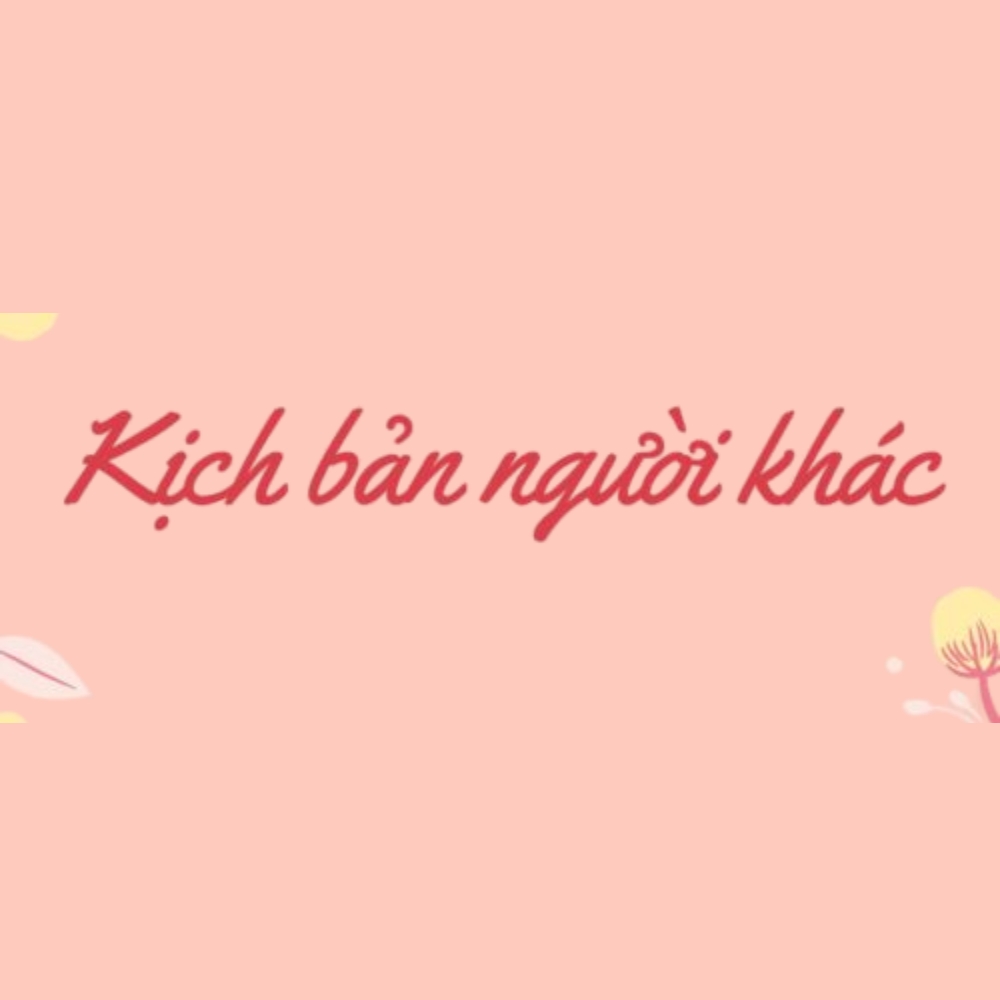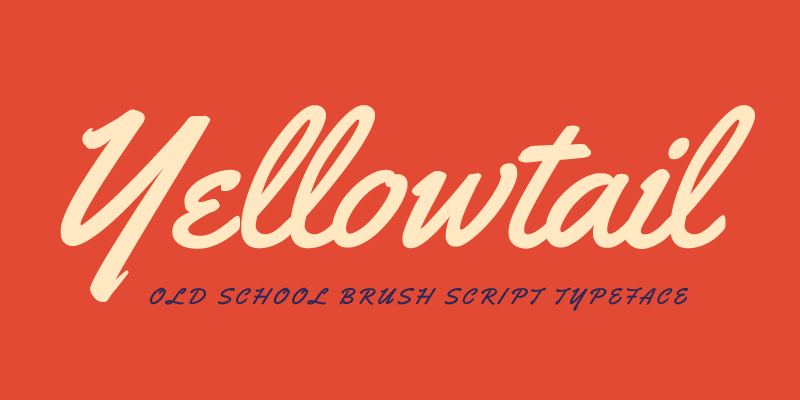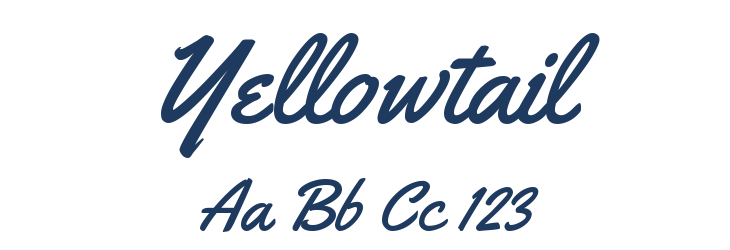
Tải 20+ font Việt hóa Yellowtail nghệ thuật và bắt mắt
Yellowtail mang đến vẻ đẹp cổ điển của những năm 1930, gợi nhớ đến phong cách vẽ bảng hiệu bằng cọ dẹt đầy tính nghệ thuật. Sự kết hợp giữa những đường nét Script nghiêng và sự dứt khoát của nét cọ đã tạo nên một bộ font chữ có sức hút riêng, vừa phóng khoáng vừa chỉn chu. Sự ra đời của font Việt hóa Yellowtail giúp các nhà sáng tạo tại Việt Nam có thêm một lựa chọn hoàn hảo cho các thiết kế mang hơi hướng hoài cổ mà không lo ngại về vấn đề lỗi ký tự tiếng Việt.
Sự độc đáo trong cấu trúc của font Việt hóa Yellowtail
Nét đặc trưng của Yellowtail nằm ở phong cách brush script với các đường nối ký tự mượt mà, tạo nên một dòng chảy văn bản tự nhiên như được viết tay bởi những nghệ nhân vẽ biển hiệu chuyên nghiệp. Font Việt hóa LNTH Yellowtail đã được tinh chỉnh bộ dấu tiếng Việt một cách khéo léo, đảm bảo các dấu thanh không làm phá vỡ cấu trúc nghiêng đặc trưng của bộ chữ. Điều này giúp văn bản luôn giữ được sự cân đối và tính thẩm mỹ cao trên mọi ấn phẩm thiết kế.
Bên cạnh đó, độ dày của nét chữ trong Yellowtail được tính toán để mang lại khả năng hiển thị ổn định. Dù được sử dụng ở kích thước lớn trên các bảng hiệu hay kích thước nhỏ trong các bản in, font chữ này vẫn giữ được độ sắc sảo và dễ đọc. Đây là phương án phù hợp cho những ai muốn tìm kiếm sự giao thoa giữa nét đẹp truyền thống và hơi thở hiện đại trong các sản phẩm đồ họa và kiến trúc.
Font Việt hóa LNTH Yellowtail đẹp 01
Font Việt hóa LNTH Yellowtail đẹp 02
Phân loại phong cách Flat-brush Script / Vintage
Phiên bản Việt hóa LNTH (Linh Nguyen Thai Hoa)
Mục đích phù hợp Logo, Bảng hiệu, Poster, Decor nội thất
Gợi ý phối hợp: Font LNTH Yellowtail Việt hóa có cá tính mạnh và nét chữ nghiêng. Để đạt được sự hài hòa trong bố cục, bạn nên phối hợp font này cùng các kiểu chữ không chân tối giản cho phần nội dung chi tiết. Sự tương phản giữa nét cọ bay bổng và sự gọn gàng của font phụ sẽ tạo nên một tổng thể chuyên nghiệp và tinh tế.
03 Ứng dụng font Việt hóa LNTH vào thực tế xây dựng
Nhờ vẻ ngoài giàu tính thẩm mỹ và phong cách hoài cổ đặc trưng, bộ font chữ này mang lại giá trị thực tế cao khi được đưa vào các hạng mục trang trí và nhận diện công trình:
• Bảng tên khu homestay nghỉ dưỡng: Những nét chữ nghiêng của Yellowtail rất ăn ý khi xuất hiện trên bảng hiệu gỗ hoặc mica gương tại các khu nhà lắp ghép, homestay container. Font chữ này giúp không gian toát lên vẻ mộc mạc nhưng vẫn sang trọng và chuyên nghiệp.
• Thiết kế logo và bộ nhận diện văn phòng: Sử dụng font Việt hóa LNTH cho tên thương hiệu trên các vật phẩm quà tặng hoặc hồ sơ năng lực giúp doanh nghiệp tạo được ấn tượng về sự sáng tạo và cá tính riêng biệt đối với đối tác và khách hàng.
• Quotes trang trí không gian nội thất: Bạn có thể dùng font Yellowtail để cắt chữ nổi laser hoặc in decal trang trí tường tại các quán cafe, sảnh chờ văn phòng nhằm tạo điểm nhấn mềm mại và khơi gợi cảm hứng cho không gian làm việc.
Font Việt hóa LNTH Yellowtail đẹp 03
Font Việt hóa LNTH Yellowtail đẹp 04
03 Lưu ý quan trọng khi trình bày bố cục với font Yellowtail
Để khai thác hiệu quả vẻ đẹp của dòng font brush script này mà không làm rối mắt người xem, người thiết kế nên lưu tâm một số kinh nghiệm sau:
• Tránh viết hoa toàn bộ ký tự: Đặc trưng của Yellowtail là nét nối mượt mà giữa các chữ thường. Việc viết hoa toàn bộ cụm từ sẽ làm mất đi nhịp điệu tự nhiên, khiến câu văn trở nên rời rạc và khó nhận diện mặt chữ.
• Điều chỉnh khoảng cách dòng hợp lý: Do nét chữ có độ nghiêng và vươn rộng, bạn nên để khoảng cách dòng thoáng một chút để các dấu tiếng Việt và nét uốn lượn không bị chồng chéo lên nhau.
• Kiểm soát độ phân giải khi in ấn: Để giữ được vẻ đẹp của những vết cọ vẽ dẹt, hãy đảm bảo tệp thiết kế đạt độ phân giải cao, đặc biệt khi triển khai in ấn trên các khổ lớn như bảng hiệu hay banner sự kiện.
Font Việt hóa LNTH Yellowtail đẹp 05